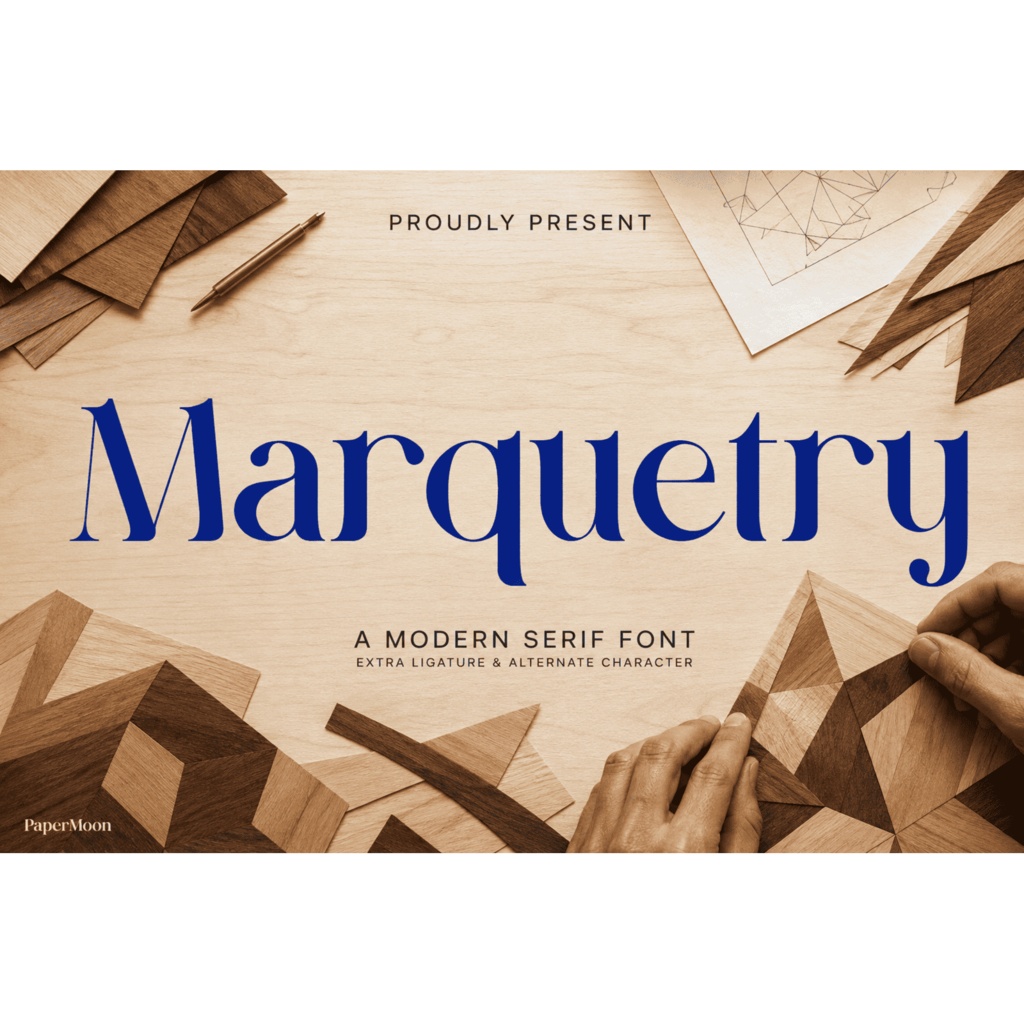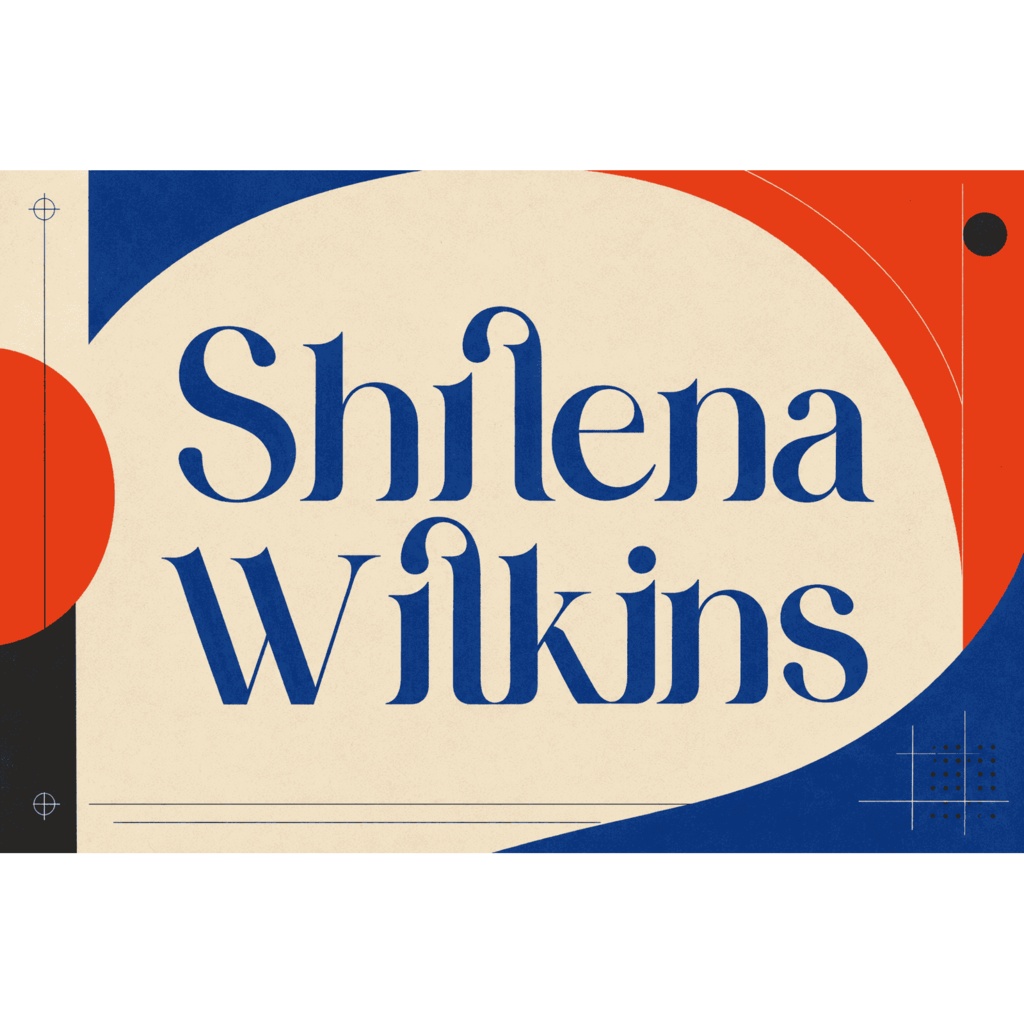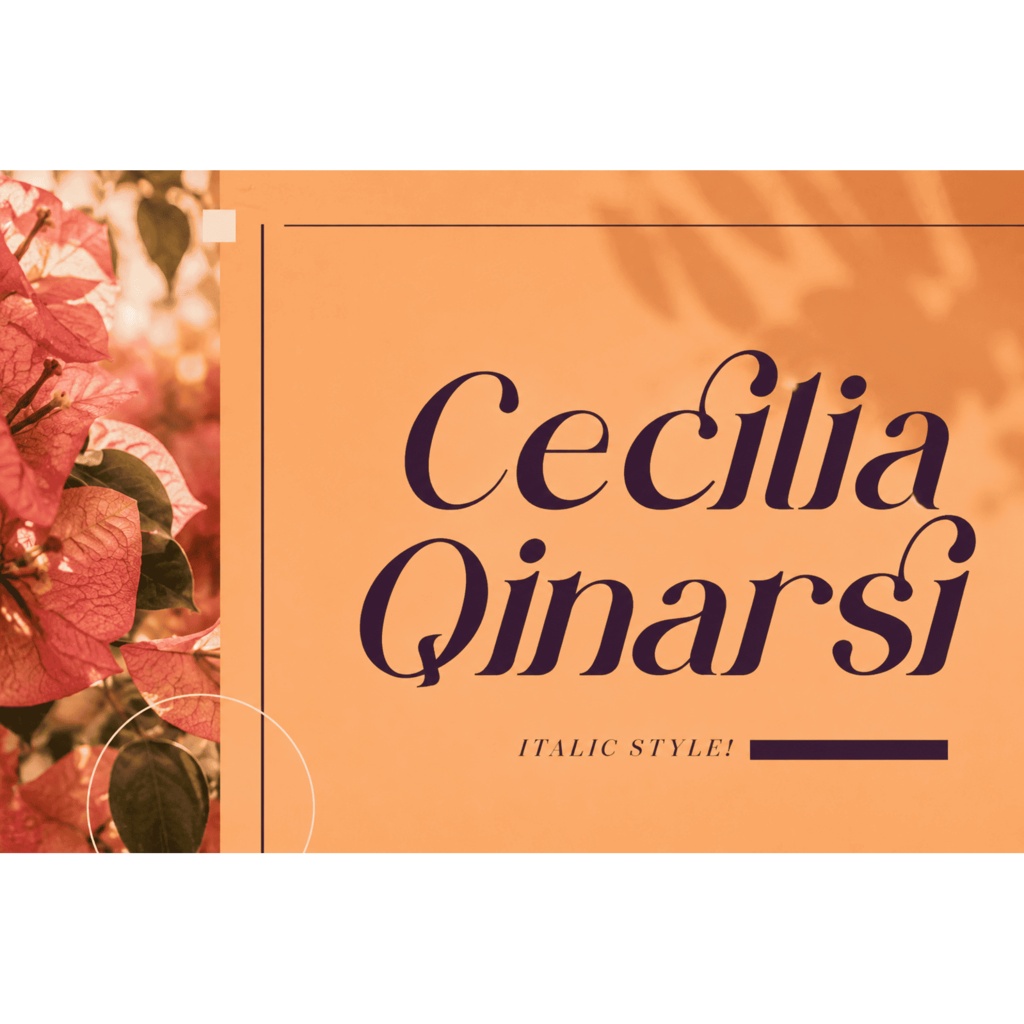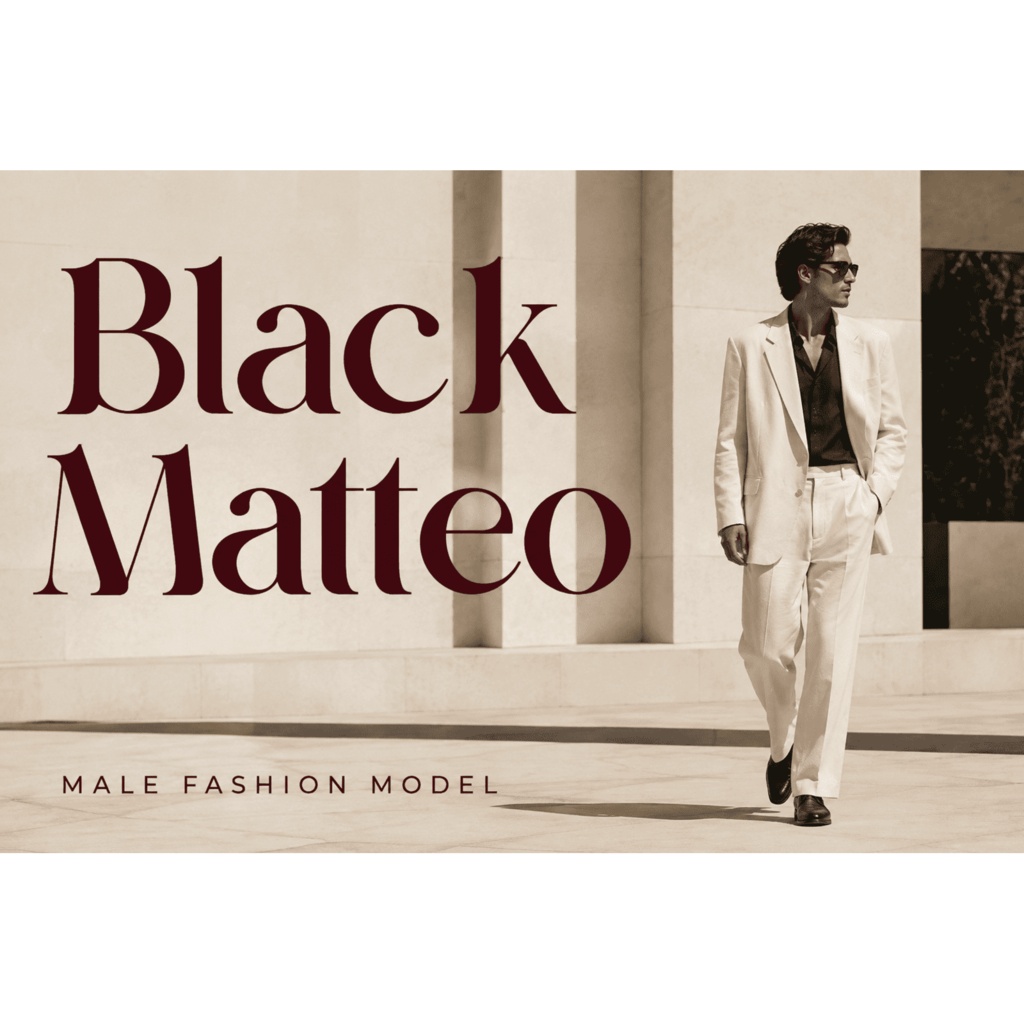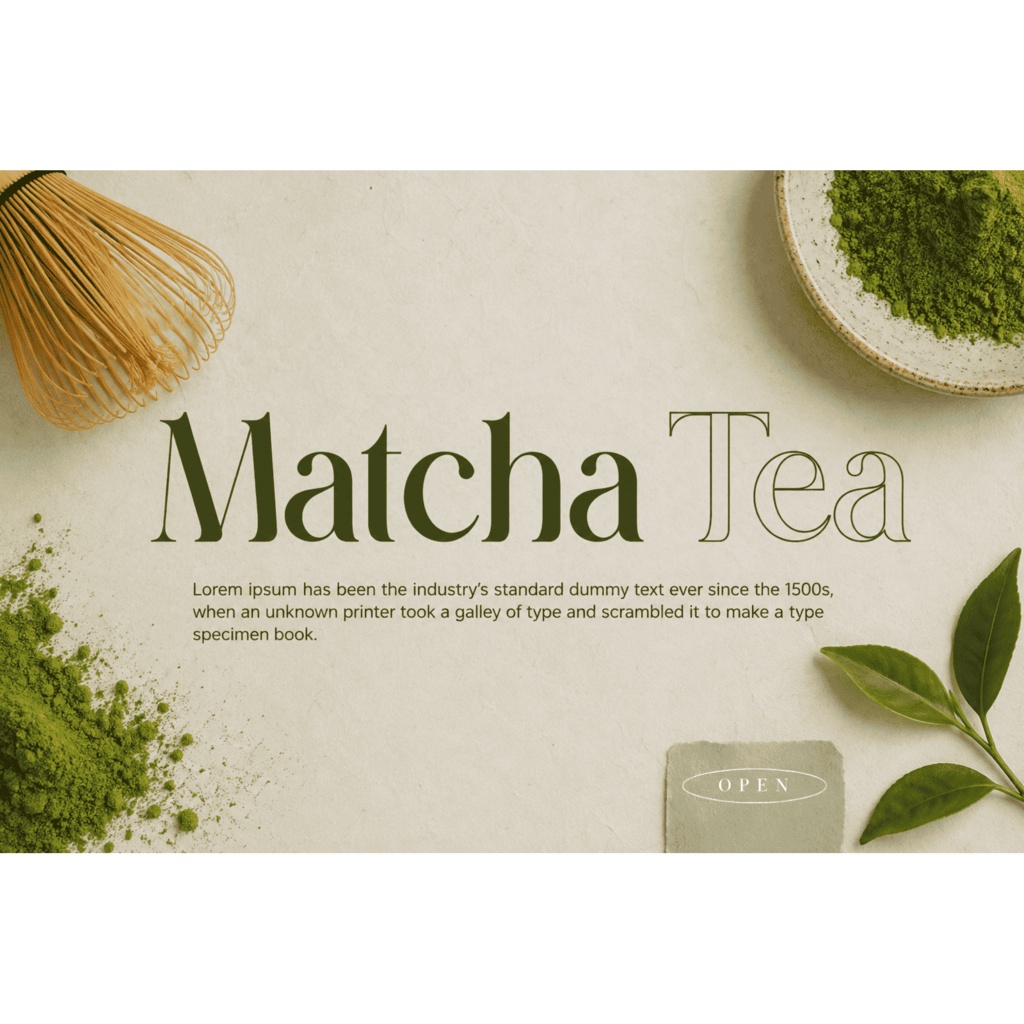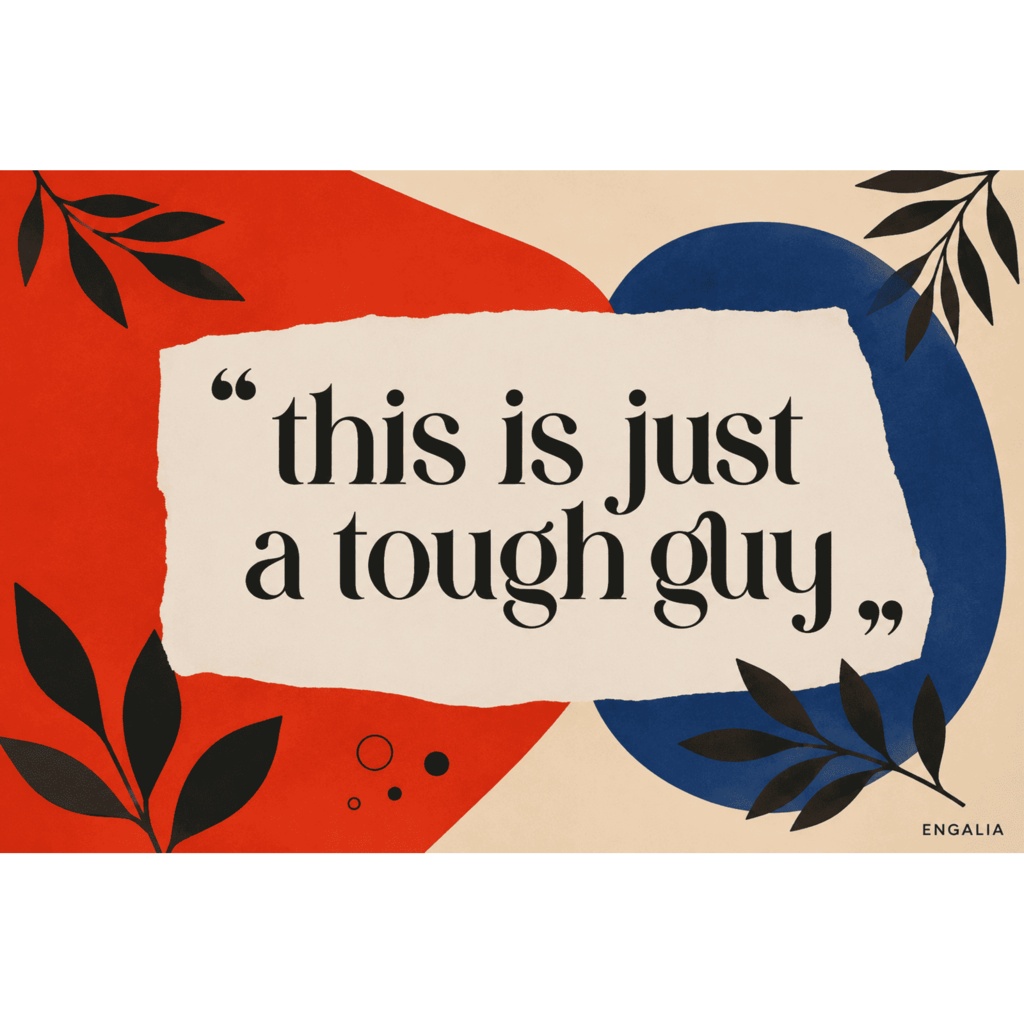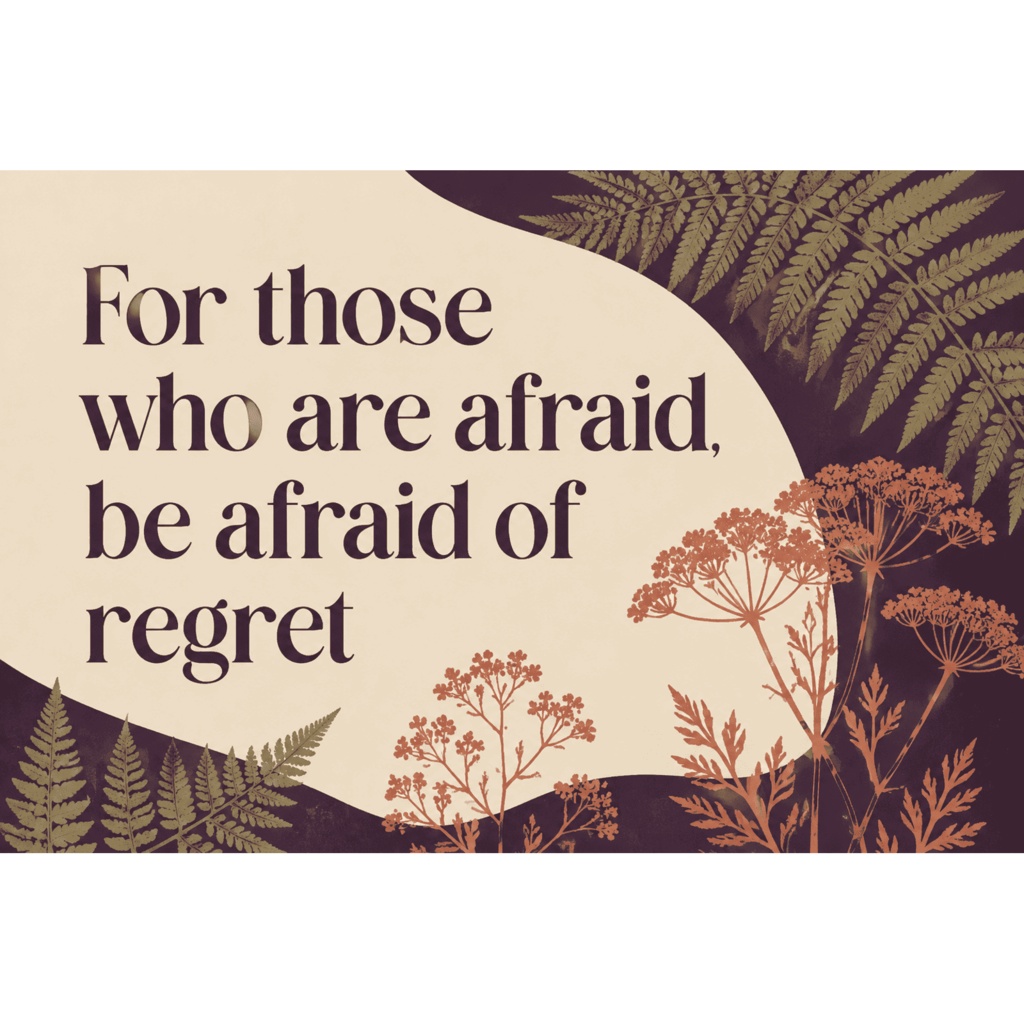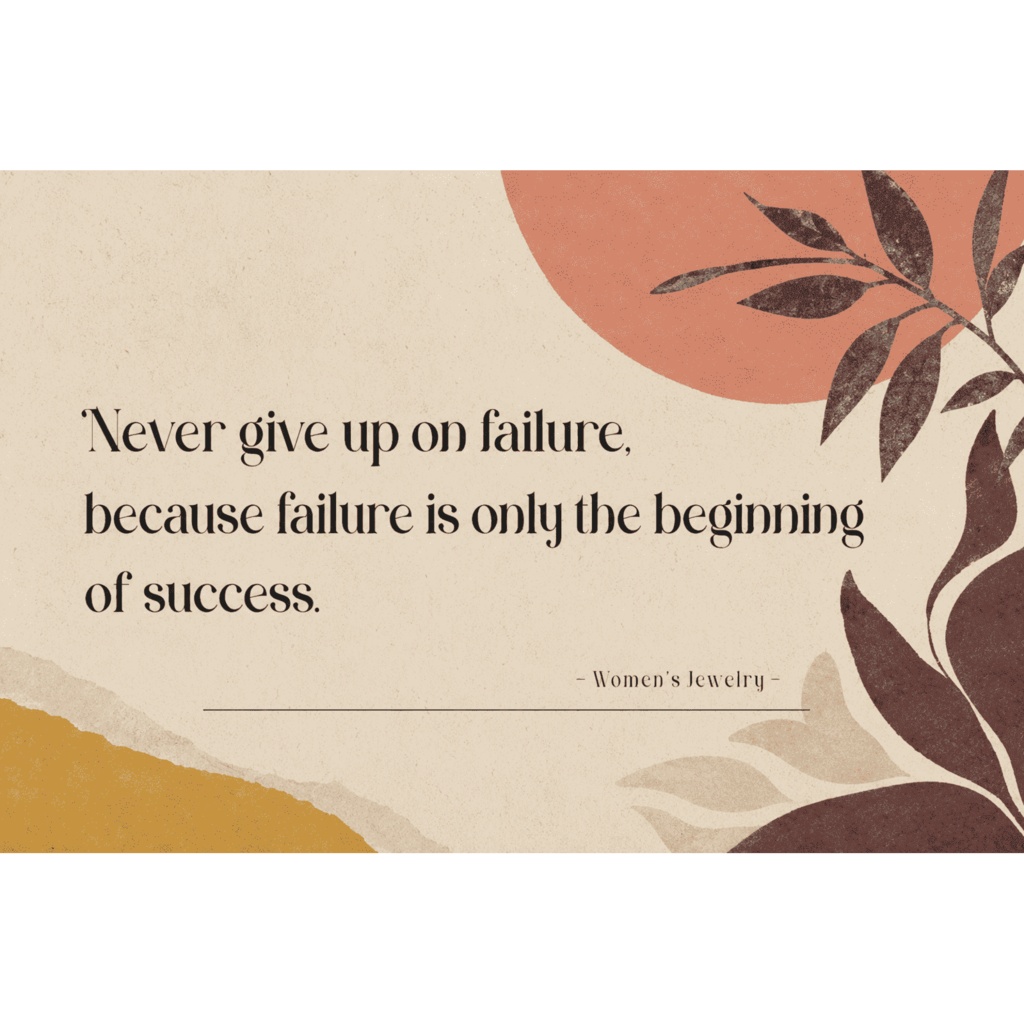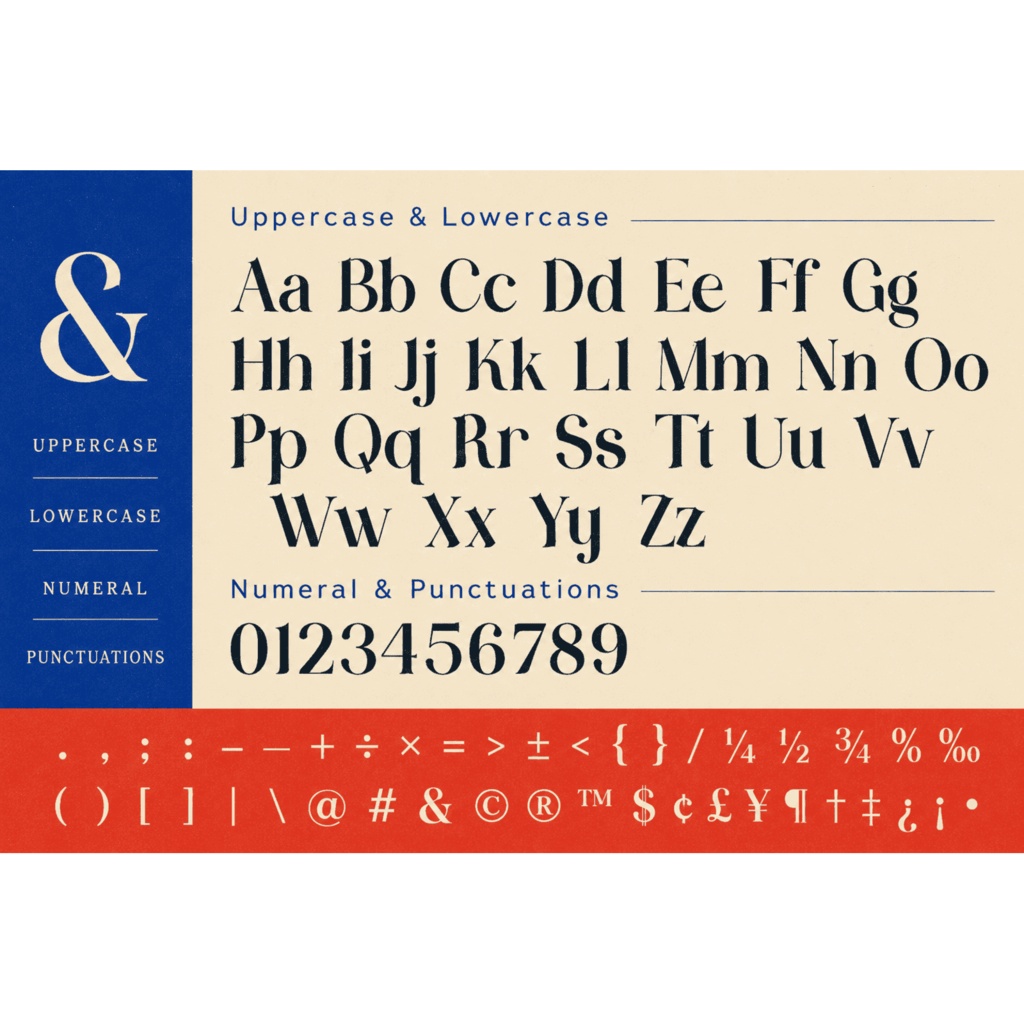
MARQUETRY | モダン・エレガントな欧文セリフフォント(Display Serif)| ロゴ・ブランディング用
MARQUETRY(マーケトリー)は、モダンでエレガントなプレミアム・セリフフォントのデュオ(Font Duo)です。正体(Regular)とイタリック(Italic)の2スタイルで構成され、ロゴ、ブランディング、高級パッケージ、招待状など、品格のあるディスプレイ表現に向いています。洗練されたセリフ(明朝系欧文)の骨格に、表情のあるイタリックを組み合わせることで、ひとつのデザインシステムのなかで上品なコントラストを生み出せます。 Regularでブランド名や見出しを自信を持って見せ、Italicでエンファシス、引用、キャプション、招待状のセカンドラインなどに動きを加えるのがおすすめです。短いフレーズやネーム、見出しに個性を持たせたいブランド・編集・パッケージデザインに特に効果的な、ディスプレイ向け(display typeface)のフォントです。 収録内容 / Included - MARQUETRY Regular / Italic の2スタイル(Font Duo) - 各スタイル 276グリフ・279マッピング文字 - OpenType機能:標準合字(liga)・スタイリスティック代替(salt)・カーニング(kern) - OTF / TTF / WOFF / WOFF2 の4形式 対応文字 / Character Set - Basic Latin(A–Z / a–z)、数字、句読点・記号、Latin-1アクセント付き文字、Latin Extended 7文字に対応しています。 - 本製品はラテン文字(欧文)専用です。日本語・キリル文字・ギリシャ文字は収録されていません。日本語レイアウトの際は、お使いの日本語フォントと併用してください。 用途 / Uses - ロゴ・ブランドロゴ / Logos and brand marks - ブランディング・高級パッケージ / Branding and luxury product packaging - ラベル・ショッピングバッグ・マグカップ・Tシャツ・ホームウェア / Labels, shopping bags, mugs, t-shirts, homewares - ポスター・名言(クォート)・ブックカバー / Posters, quotes, book covers - 名刺・招待状・グリーティングカード・ウェディング / Business cards, invitations, greeting cards, wedding stationery - 写真の透かし・特別イベント・ラグジュアリーなブランド素材 / Photography watermarks, special events, luxury brand material 形式 / Formats - OTF / TTF(デスクトップデザイン用) - WOFF / WOFF2(Webフォント用、@font-face設定が必要です) 対応環境 / Compatibility - PC・Mac対応。OTF / TTF をサポートするアプリケーション(Adobe Photoshop・Illustrator・InDesign、Canva、Procreate、Figma、Affinity、Microsoft Word、Cricut Design Space、Silhouette Studio など)で利用できます。 - OpenType機能の利用可否はアプリケーションにより異なります。合字や代替字形はOpenType対応ソフトでご利用ください。 利用許諾 / License - 商用利用可能なProパッケージです。クライアントワーク、ブランディング、マーケティング、デジタルデザイン、物理商品、販売用商品への利用は、同梱の商用フォントライセンス(PaperMoon)の定めに従って認められています。 - フォントファイル単体での再配布・転売・共有は禁止です。詳細な条項は出品ページのライセンス表記をご確認ください。